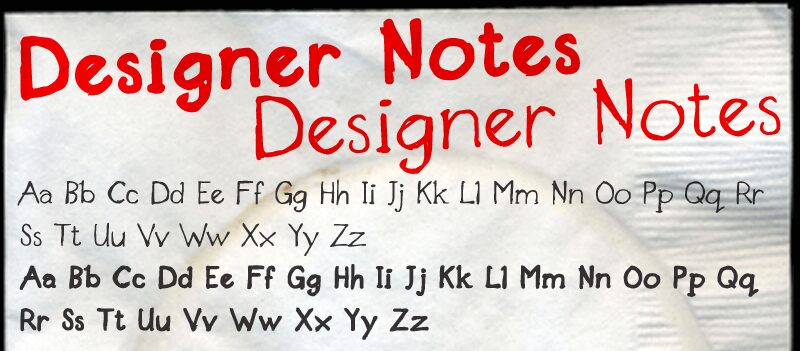
Designer Notes von CampPhotoshop ist eine kostenlose, handgeschriebene Schrift, die den lockeren, persönlichen Vibe schneller Marker-Notizen einfängt. Die Buchstaben basieren auf ungleichmäßigen Schwüngen und leicht ausgefransten Strichen, was für einen Notizbuch-Charakter sorgt: informell, menschlich und eher skizzenhaft statt perfekt ausgearbeitet.
Diese kostenlose Schrift eignet sich ideal für Projekte, die einen lässigen Ton erfordern – von Notizbuch-Covern und Scrapbook-Titeln bis hin zu Café-Menüs, Klassenzimmer-Postern, Grußkarten und kurzen Social-Media-Überschriften. Sie glänzt besonders in kurzen Displaysatz-Anwendungen, wo ihr lebendiger Rhythmus und die handgezeichnete Textur voll zur Geltung kommen, vor allem bei Titeln, Cover-Lines und Namen.
Ich skizziere und mache meine Notizen mit einem Pilot Precise V5RT Stift.